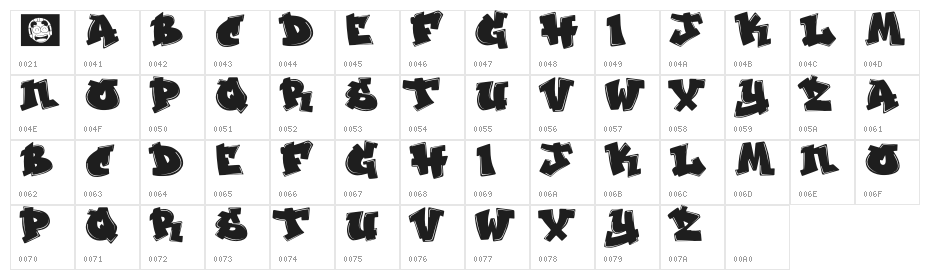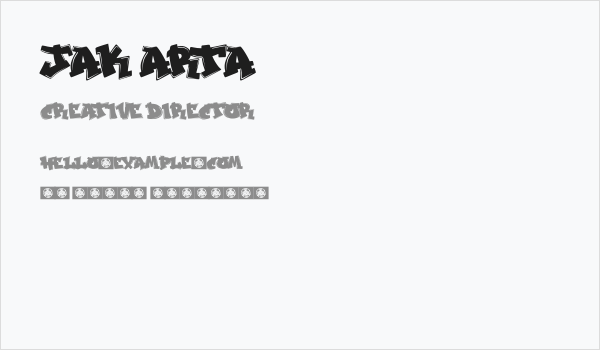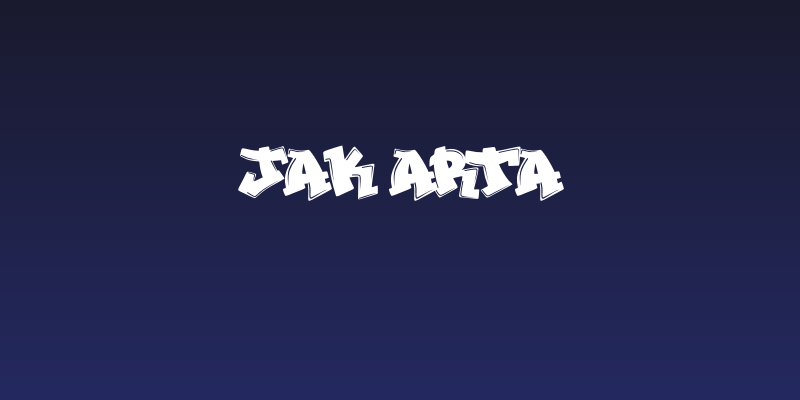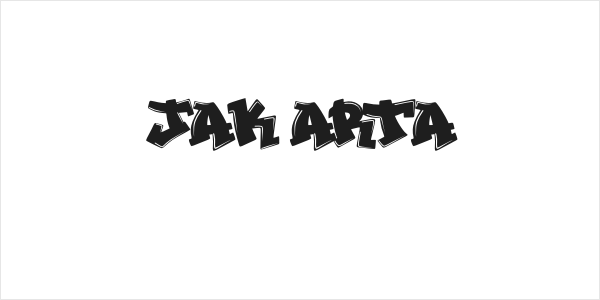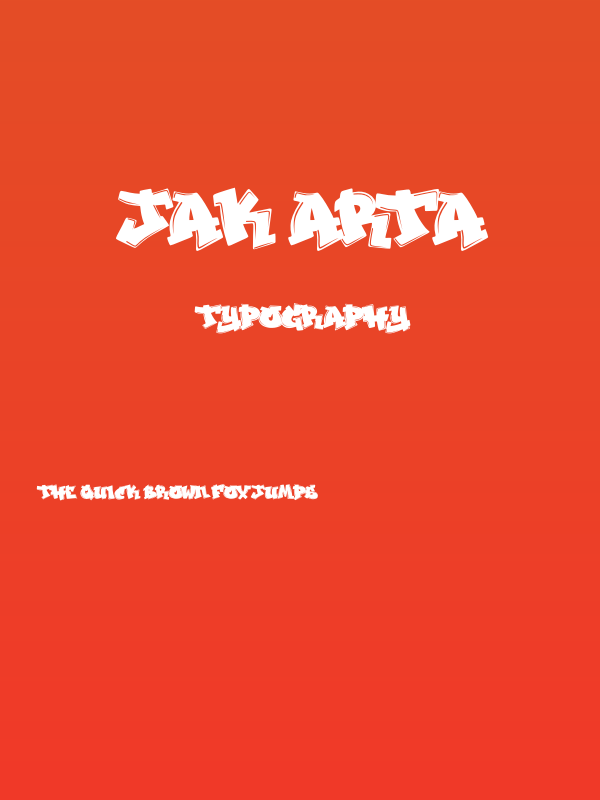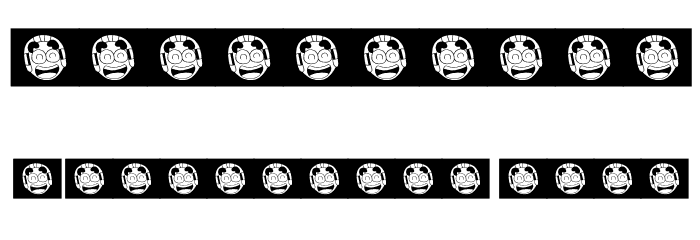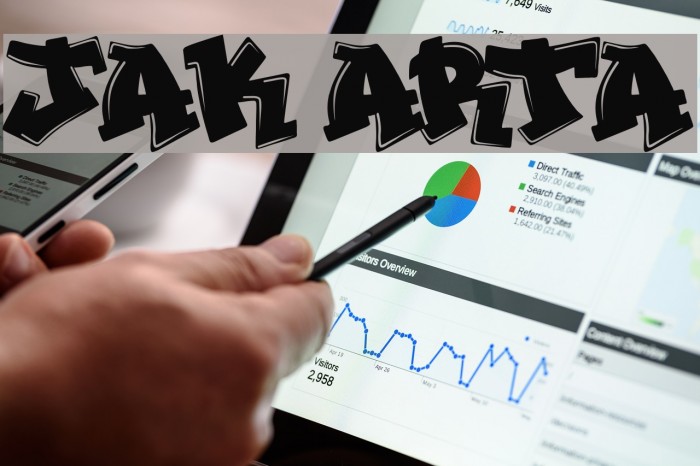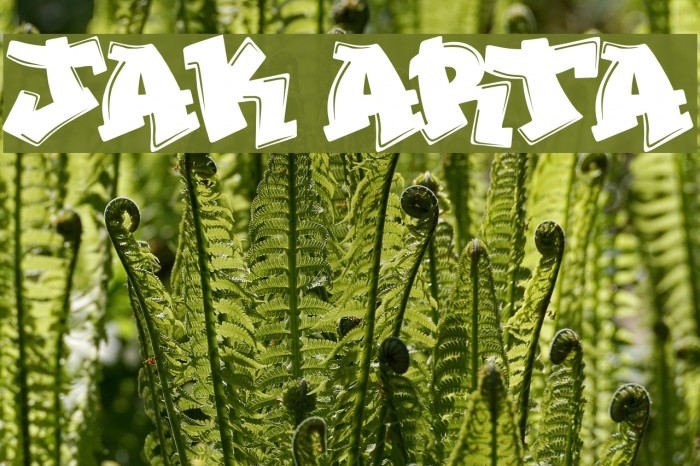
JAK ARTA Font
✎ Graffiti
| 全体的なスタイル | Urban, Edgy, Graffiti |
| おすすめプロジェクト | Ideal for street art designs, urban-themed posters, music album covers, and edgy branding projects. |